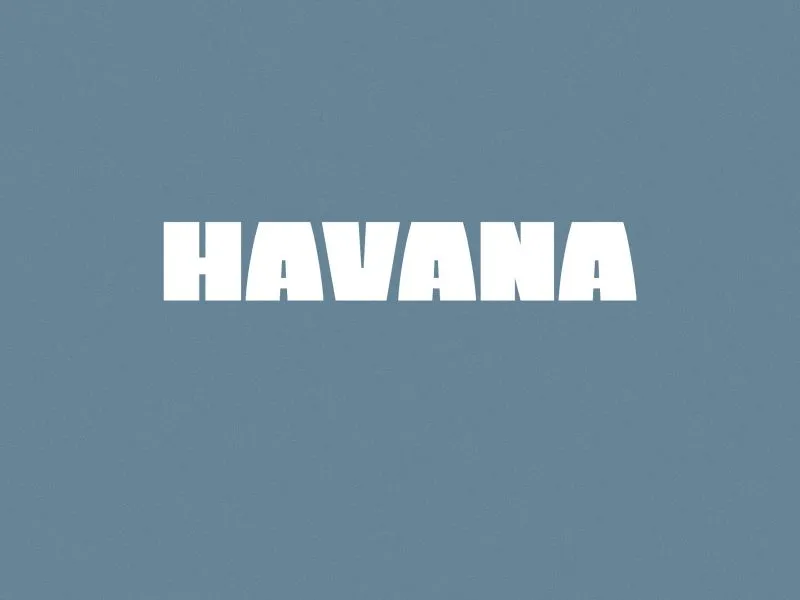
Aqui está uma versão de dois parágrafos para a descrição da fonte Havana Bold Sans Serif Font: Havana é uma fonte sans serif moderna e robusta que traz um clima vintage acolhedor. Perfeita para os ambientes digitais atuais, Havana se destaca na categoria das fontes de letra sem serífera. Seu design cuidadoso visa acompanhar as tendências da atualidade, oferecendo uma textura desbotada que transmite um look antigo e despojado sem a necessidade de usar técnicas de fotocopiagem mais elaboradas. Ideal para criações em zines e anúncios modernos, Havana é ideal para estilos digitais que valorizam um visual quase “aula de história” na tela, mantendo o aspecto antigo do papel impresso sem a necessidade de técnicas complexas.